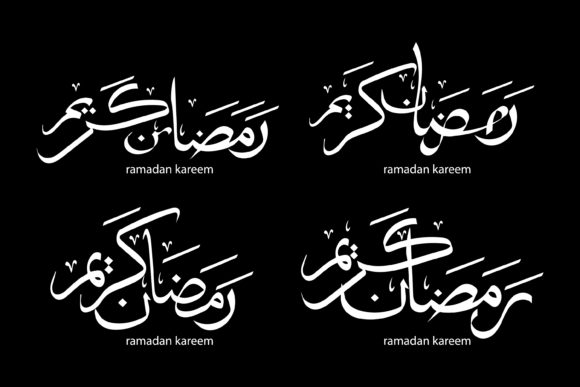
Ramadan Kareem Arabic Calligraphy
قد يكون العثور على عناصر التصميم المناسبة أمرًا صعبًا، ولكن Ramadan Kareem Arabic Calligraphy يقدم مجموعة استثنائية ترتقي بعملك على الفور.
تم تصميمه بدقة، ويوفر Ramadan Kareem Arabic Calligraphy متجهات نظيفة وطباعة سلسة وترخيصًا تجاريًا لراحة بالك.
سواء كنت تقوم بإنشاء منتجات الطباعة عند الطلب أو دعوات الزفاف أو رسومات وسائل التواصل الاجتماعي، فإن Ramadan Kareem Arabic Calligraphy هو الخيار المثالي.